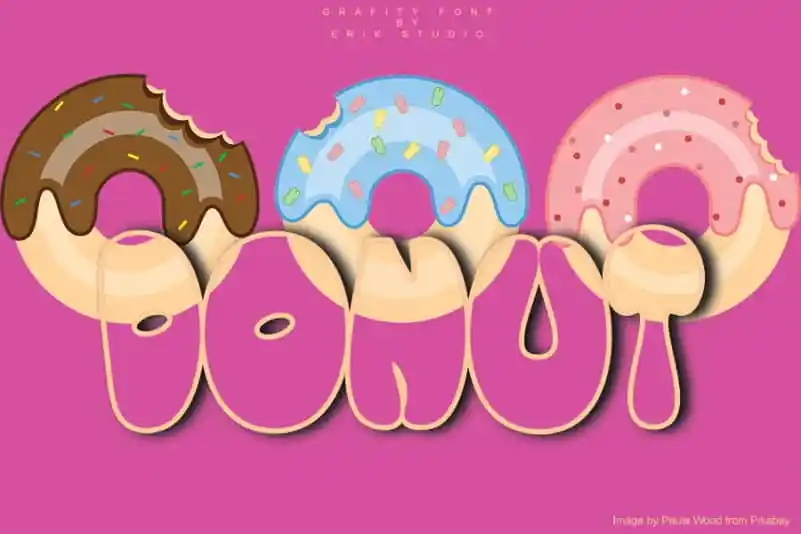
Donut Display Font
A Donut Display Font é uma seleção alegre e infantil para quem busca destaque visual na sua próxima criação digital. Embora possa parecer um design infantil, a font oferece um toque leve de inocência que combina perfeitamente com qualquer projeto que busque trazer um sorriso aos olhos do usuário. Desenvolvida por Erik Studio, esta font foi projetada para aqueles que desejam uma pitada de autenticidade e graça em suas identidades digitais. Seja para cartazes de eventos alegres ou design gráfico jovial, Donut Display é o ideal escolha para dar um toque único e encantador à sua criação.